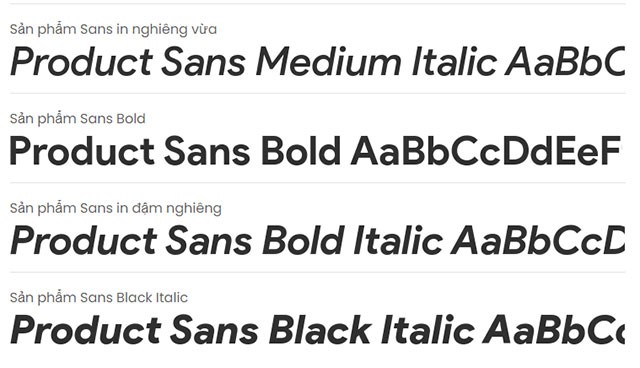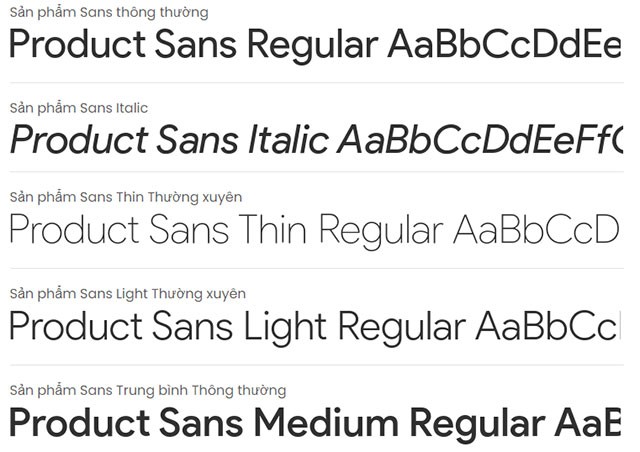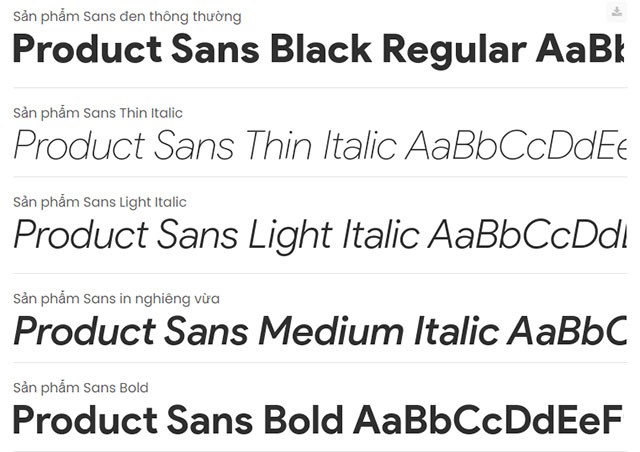
Google Sans Font - Bộ Font Chữ Google
Giới thiệu về Font chữ Google Sans
Font chữ Google Sans là bộ font chữ hiện đang được Google ưu tiên sử dụng rộng rãi trên hầu hết các nền tảng và ứng dụng của mình.
Sự phổ biến của Google Sans đến từ thiết kế tối giản, các đường nét chữ sắc sảo và rõ ràng.
Khoảng cách giữa các ký tự được cân đối, mang lại cảm giác dễ chịu và thoải mái cho người đọc.
Việc sử dụng Google Sans sẽ giúp bài viết của bạn trở nên chuyên nghiệp và thân thiện hơn với người đọc.
Các font chữ trong Bộ font chữ Google Sans
Các biến thể trong Bộ font chữ Google Sans
• Product Sans Regular
• Product Sans Italic
• Product Sans Thin Regular
• Product Sans Light Regular
• Product Sans Medium Regular
• Product Sans Black Regular
• Product Sans Thin Italic
• Product Sans Light Italic
• Product Sans Medium Italic
• Product Sans Bold
• Product Sans Bold Italic
• Product Sans Black Italic
Đặc biệt, đối với những người hoạt động trong lĩnh vực thiết kế đồ họa và xây dựng website, đây là bộ font chữ hàng đầu, mang đến cảm giác thân thiện mà bất kỳ ai cũng dễ dàng yêu thích.
Google Sans là bộ font chính thức do Google phát triển, được tích hợp trên nhiều sản phẩm của Google, từ các nền tảng web đến các ứng dụng di động.
Google Sans là bộ font chữ gì?
Google Sans là bộ font chữ hiện đang được Google sử dụng rộng rãi trên các ứng dụng của mình. Bộ font này được thiết kế với vẻ ngoài đơn giản, hiện đại và dễ đọc.
Bộ Google Sans bao gồm những kiểu chữ nào?
Bộ Google Sans hiện có các kiểu chữ như: Product Sans Regular, Italic, Thin Regular, Light Regular, Medium Regular, Black Regular, Thin Italic, Light Italic, Medium Italic, Bold, Bold Italic và Black Italic.
Lợi ích của việc sử dụng bộ font Google Sans là gì?
Google Sans là bộ font phổ biến, được ưa chuộng trong thiết kế đồ họa và website nhờ khả năng mang lại cảm giác thân thiện, dễ đọc cho người xem.
Google Sans thường được sử dụng trong những trường hợp nào?
Google Sans là bộ font chữ được Google sử dụng rộng rãi trên các nền tảng của mình, bao gồm cả website và ứng dụng di động. Font chữ này giúp tạo nên diện mạo nhất quán và hiện đại cho các sản phẩm của Google.